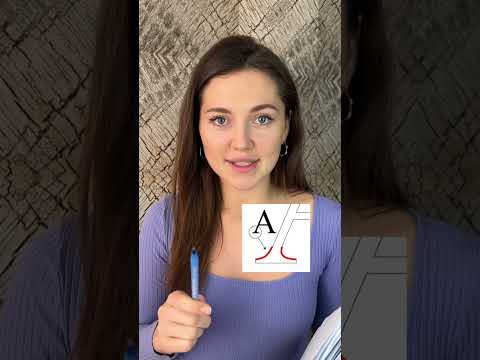
Уникальным образом оформляйте свои тексты с помощью современных шрифтов на кириллице
В данной статье вы найдете советы и идеи по выбору и использованию современных шрифтов с засечками для написания эффектных и читаемых кириллических надписей на различных материалах и визуальных материалах.
Выбирайте шрифты, которые сочетают в себе современный стиль и хорошую читабельность. Обратите внимание на разные насыщенности и толщины засечек, чтобы достичь желаемого эффекта.
Используйте шрифты с засечками для создания эффектных заголовков и акцентных элементов в дизайне. Они добавят интерес и уникальность вашим текстам.
Экспериментируйте с разными комбинациями шрифтов с засечками, чтобы создать гармоничный и современный вид ваших надписей. Объединение разных стилей шрифтов может привести к необычным и интересным результатам.